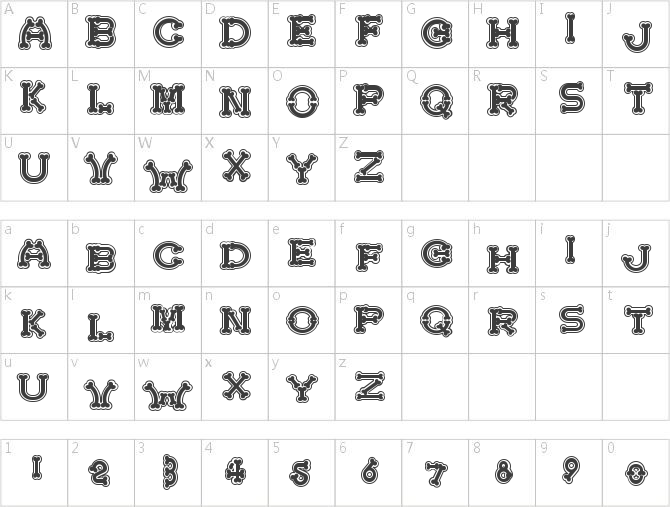
Bonecracker college
Bonecracker college介紹
Bonecracker college字體字庫是一款讓人賞心悅目、百看不厭的英文字體,適合各類廣告和產(chǎn)品包裝設計應用,字體大小0.46MB,格式為ttf字體,上傳用戶是釜源貿(mào)易,作者/版權(quán)方為未知